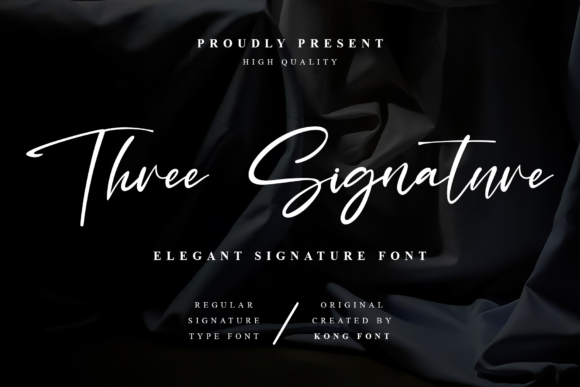
Three Signature
Three Signatureのような高品質の素材をお探しの場合、このプレミアムパッケージはクリエイティブなプロジェクトに素晴らしい選択です。
精密に作られたThree Signatureは、クリーンなベクター、滑らかなタイポグラフィ、そして安心のための商用ライセンスを提供します。
POD(オンデマンド印刷)製品、結婚式の招待状、またはソーシャルメディアのグラフィックを作成している場合でも、Three Signatureは理想的です。